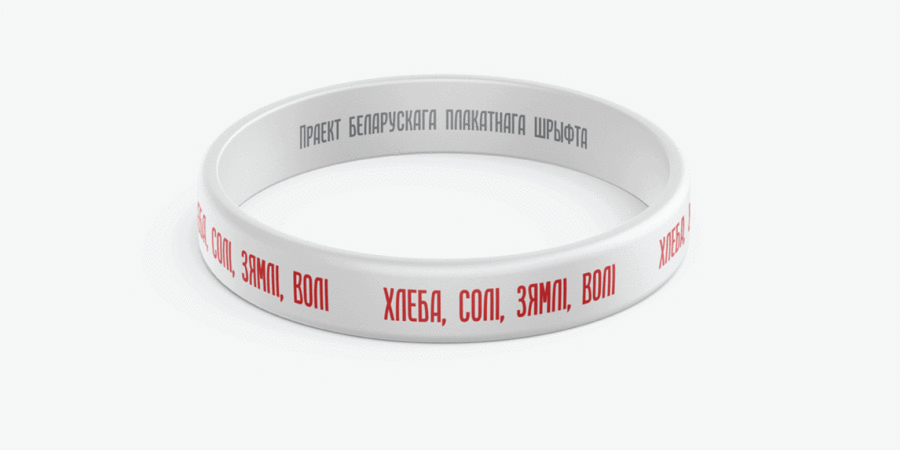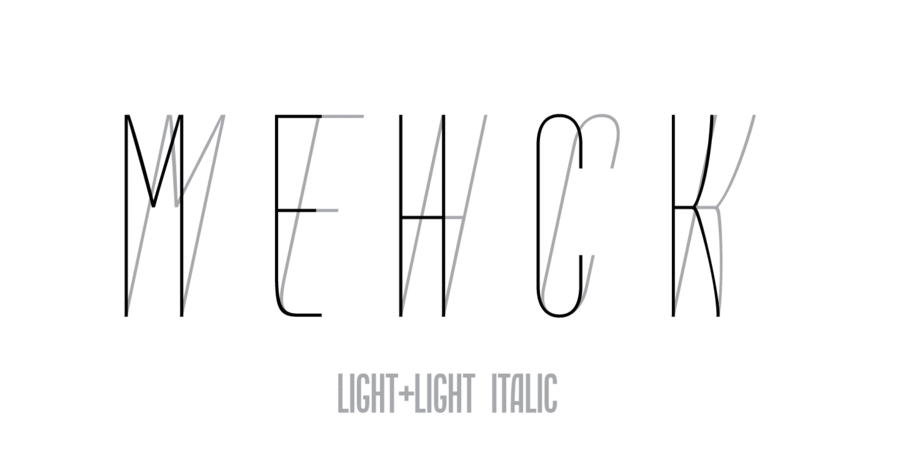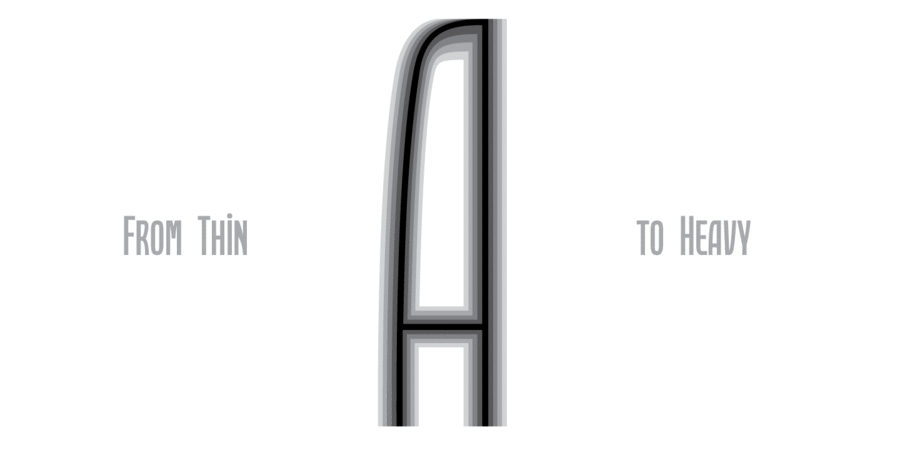
Гарнітура Хлеба Солі Зямлі Волі – це графічне дослідження, що об'єднує традиційний грубий жирний плакатний шрифт з гуманістичними нотками епохи Відродження. Гарнітура успадкувала деякі ідеї Франциска Скорини, щоб додати гуманістичний відтінок. Назва навіяна віршем Янки Купали. Це сучасний білоруський титульний плакатний шрифт, але його можна легко використовувати в будь-яких випадках, коли необхідно поєднувати строгі лінії традиційних плакатів з гуманістичним стилем. Сімейство шрифтів має 5 насичень і 5 нахилених накреслень. Написи цим шрифтом утворюють суцільний блок. Накреслення Heavy є безкоштовним для комерційного та некомерційного використання, за ліцензією CC BY-ND 4.0. Шрифт розробив Олексій Коваль у 2020 році.
Асоціації з сімейством шрифтів Hleba Soli Ziamli VoliОсобистість і характер гарнітури:
рівний, стрункий, худий, тонкий, легкий, стиснений, високий, міський, стійкий, стабільний, делікатний, невагомий, прозорий, дротяний, оригінальний, самобутній, характерний, цікавий, тісний, твердий, кінематографічний, чіткий, серйозний, дорослий, важливий, помітний, гучний, мотивуючий, гордий, амбітний, авторитетний, переконливий, монументальний, сильний, надійний, гнучкий, дерев'яний, важкий, потужний, чорний, наполегливий, яскравий, активний